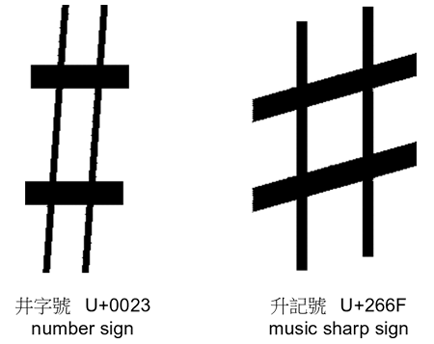
近似字符研究之二:井字号 vs. 升记号
井字号我们常看到,在计算机、电话键盘上就有,形状就像是我们中文的“井”字,因此我们一般就称呼他为井字号(number sign)。但是,如果你有看五线谱的话,会发现有一个记号和井字号很像的,那就是升记号(musical sharp sign),先不要去看这些符号,现在在你的脑子里头回想一下,这两个符号是不是一样呢?
在 Unicode 他们的码位(codepoint)是不同的,井字号是安排在 U+0023,而升记号是安排在 U+266F。现在答案揭晓,井字号是:直的是斜的,横的是平的;升记号则是:直的是直的,横的是斜的。如下图:
现在问题来了,这两个字符是那么的相像,那么会产生些微不同的设计,是有什么历史因素或是有其它的理由呢?这两个字符是不是原来有关系,后来才分歧的呢?老实说,我找了好久的 google,但不得要领,找不到这么设计的理由。后来在 TeX fonts mailing list 询问,他们也是说本来就是不同一个字符,是刚好长得很像,就如同 A 就是这样写,B 就是那样写。各位认为呢?
微软研发的一种新语言C#,到底是要怎么念?跟据微软官方的FAQ,C#不是一般人所认为的“杂凑”(或井字) 符号,实际上它应该是音乐的升记号。但是,因为在标准键盘上并没有升记号,所以将它输入成杂凑 ("#") 符号较容易。当然,语言名称的发音就是“see sharp”。